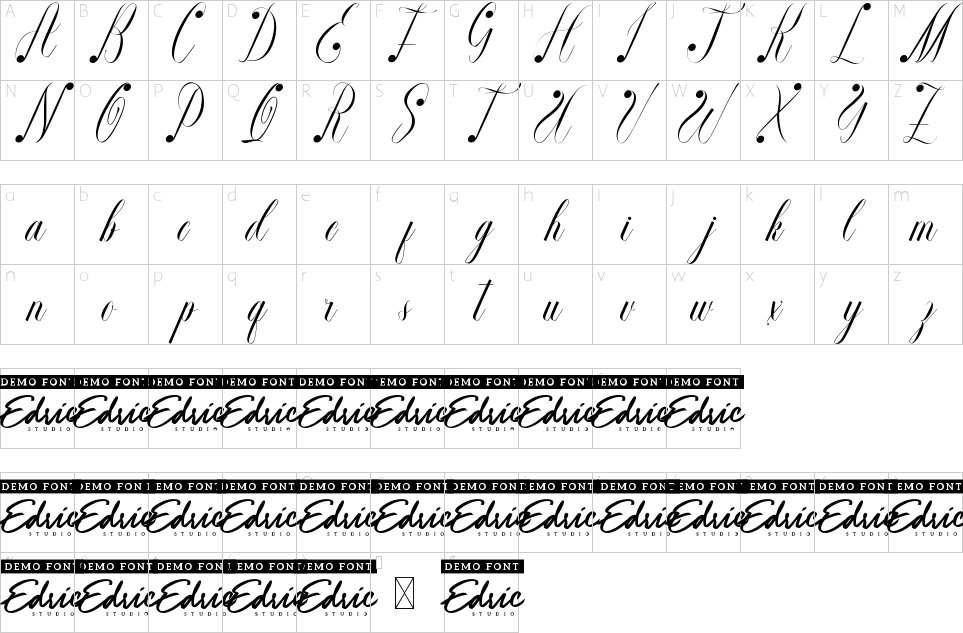
Kala Nirmala Font – Download Grátis
Descubra a beleza única da Kala Nirmala font, uma gravação gratuita que se destaca no catálogo de recursos gráficos. Desenvolvida pela EdricStudio, a Kala Nirmala não apenas oferece uma experiência visual agradável, mas também ajuda a tornar qualquer projeto design gráfico mais atraente e profissional. Com sua elegância e simplicidade, a Kala Nirmala se destaca como uma fonte que valoriza a transparência e o respeito pelo design. Seja para textos legíveis ou para adicionar um toque de personalidade a qualquer projeto, a fonte se adapta perfeitamente. Mais de 1.132 pessoas já desfrutaram de sua utilização, e agora você pode explorar suas possibilidades sem gastar nada. Descubra por si mesmo o poder da Kala Nirmala e deixe sua marca de forma elegante e eficaz.